كيفية تغيير الخط في إنستقرام للتعاليق والمنشورات ووصف البروفايل
هل سبق أن رأيت شخص ما على إنستقرام قام بالتعليق عليك بخط مختلف وغير معتاد، أو قام بكتابة وصف البروفايل الخاص به بخط مختلف أيظاً وجذاب. قد تتساءل عن كيفية القيام بذلك أنت أيظاً؟ دعنا نكشف لك كيفية تغيير الخط على instagram خطوة بخطوة حتى تتميز عن الآخرين.
بشكل افتراضي، يستخدم إنستقرام خط Proxima Nova للنصوص الصغيرة مثل التعليقات والمنشورات.
يدعم إنستقرام معظم نصوص Unicode الذي يشمل رموز حسابية ويونانية وحروف عبرية ذات أسلوب مميز في الكتابة كالتالي (𝒶 𝓈𝒸𝓇𝒾𝓅𝓉 𝒽𝒶𝓃𝒹𝓌𝓇𝒾𝓉𝓉𝑒𝓃، 𝔞 𝔰𝔱𝔶𝔩𝔢 𝔊𝔬𝔱𝔥𝔦𝔠) إضافة إلى أنواع أخرى من الكتابة التي قد تنال إعجابك. دعنا نلقي نظرة عن كيفية استخدام هذه النصوص في حسابنا إنستقرام.
كيفية إضافة خطوط مختلفة في وصف البروفايل “Bios” والمنشورات
سوف نعتمد على أحد التطبيقات من أجل كتابة نصوص Unicode بشكل أسهل وأفضل اعتماداً على عملية النسخ واللصق.اسن
افتح المتصفح على هاتفك الذكي ثم ادخل إلى موقع Coolfont ثم قم بكتابة النص الذي تريد إضافته على إنستقرام في أي مكان تريد. قم بكتابة النص في الخانة الأولى، وسوف تجد في الأسفل كيف يظهر ذلك النص بالخطوط الأخرى. سوف يظهر لك حوالي 100 خط مختلف يمكنك الاختيار فيما بينهم.
اختر الخط المناسب لك، ثم انقر على خيار Decorate في حالة إن أردت إضافة زخارف متنوعة إلى جانبي النص من أجل تزيينه. بمجرد الوصول إلى الخط والتزيين المناسب، حدد النص وانقر على نسخ “Copy”، أو بدون تزيين يمكنك النقر ببساطة على زر Copy الموجود في الجانب.
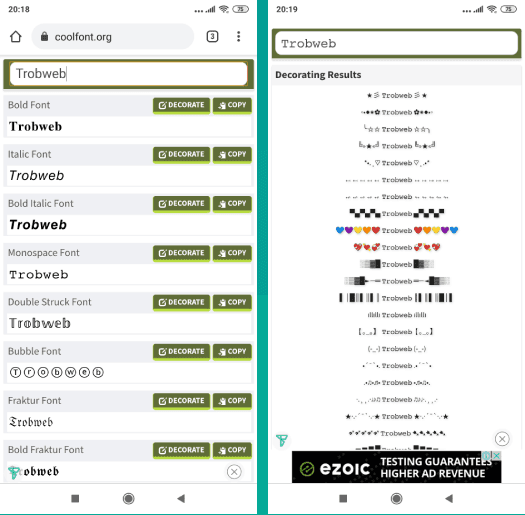
بعد نسخ النص، توجه إلى حسابك إنستقرام من أجل لصقه في أي مكان أردت. على سبيل المثال سوف نقوم بلصق النص في وصف البيو للبروفايل كما هو مبين في الصورة أدناه.
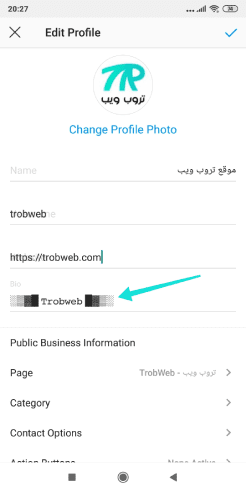
بغض النظر عن وصف البروفايل والمنشورات، يمكنك أيظاً إضافة هذه الخطوط إلى قصص إنستقرام بدون أي قيد. ويجدر الذكر أن قصص إنستقرام مضمنة ببعض من الخطوط المتنوعة بشكل رسمي، لذلك في حالة إن لم تعجبك، يمكنك استخدام هذه الطريقة طبعاً لإضافة خطك المناسب.
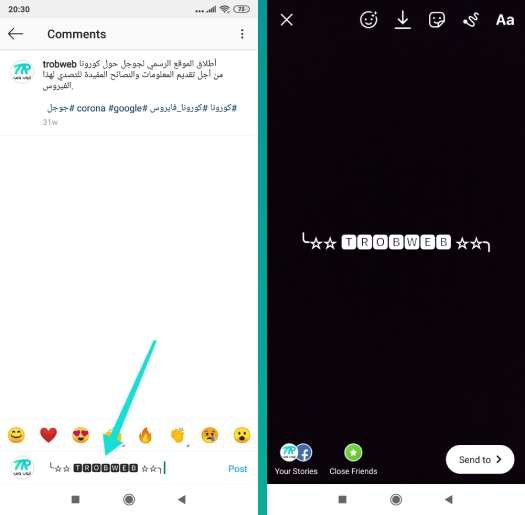
كان هذا كل ما في الأمر، يمكنك القيام بهذه الخطوات من أجل إضافة لمسة من الرونق والتميز لحسابك إنستقرام بكل بساطة. تجدر الإشارة أنه يمكنك الاعتماد على نفس الطريقة للصق النصوص على حساباتك في الشبكات الاجتماعية الأخرى، مثل فيسبوك، تويتر، واتس اب.